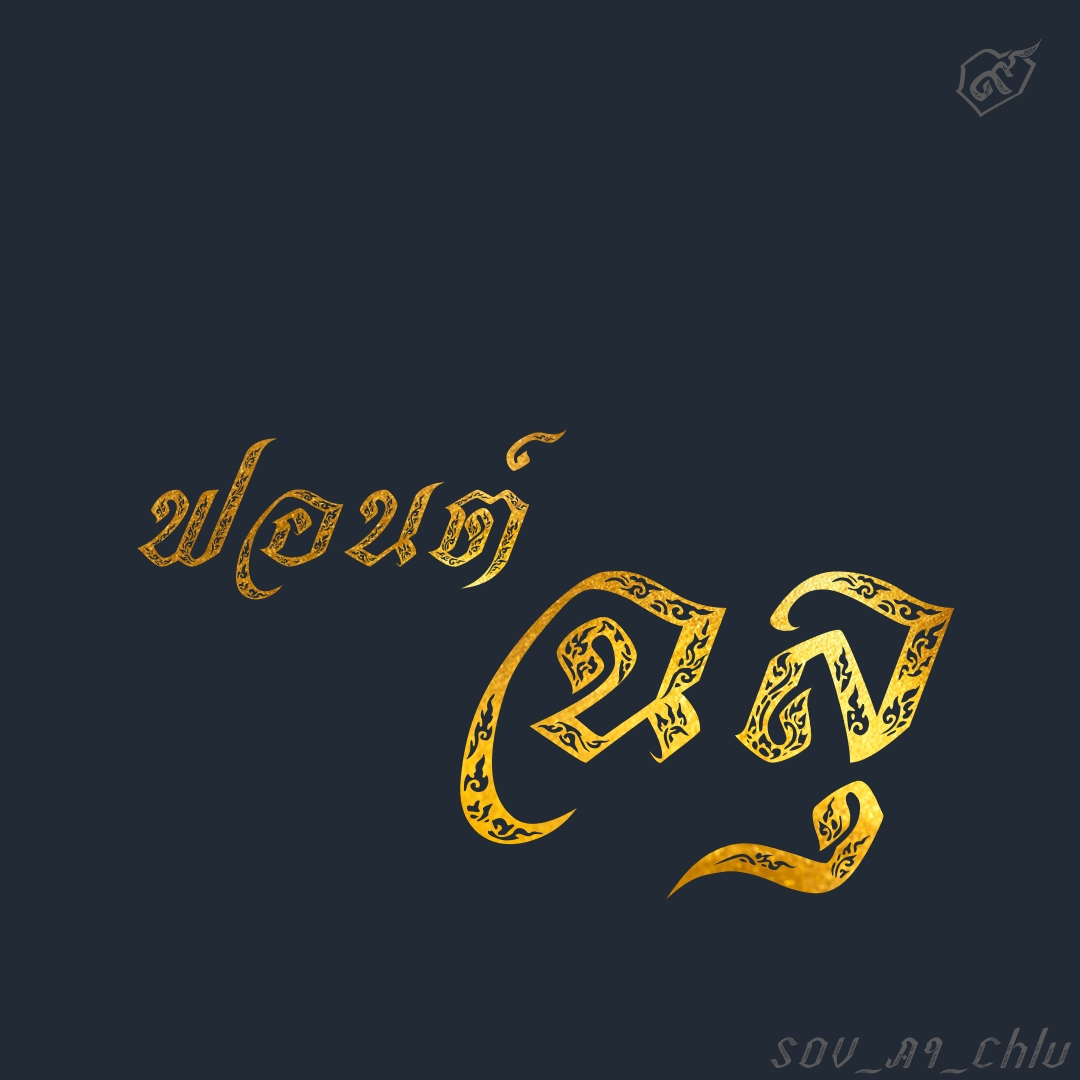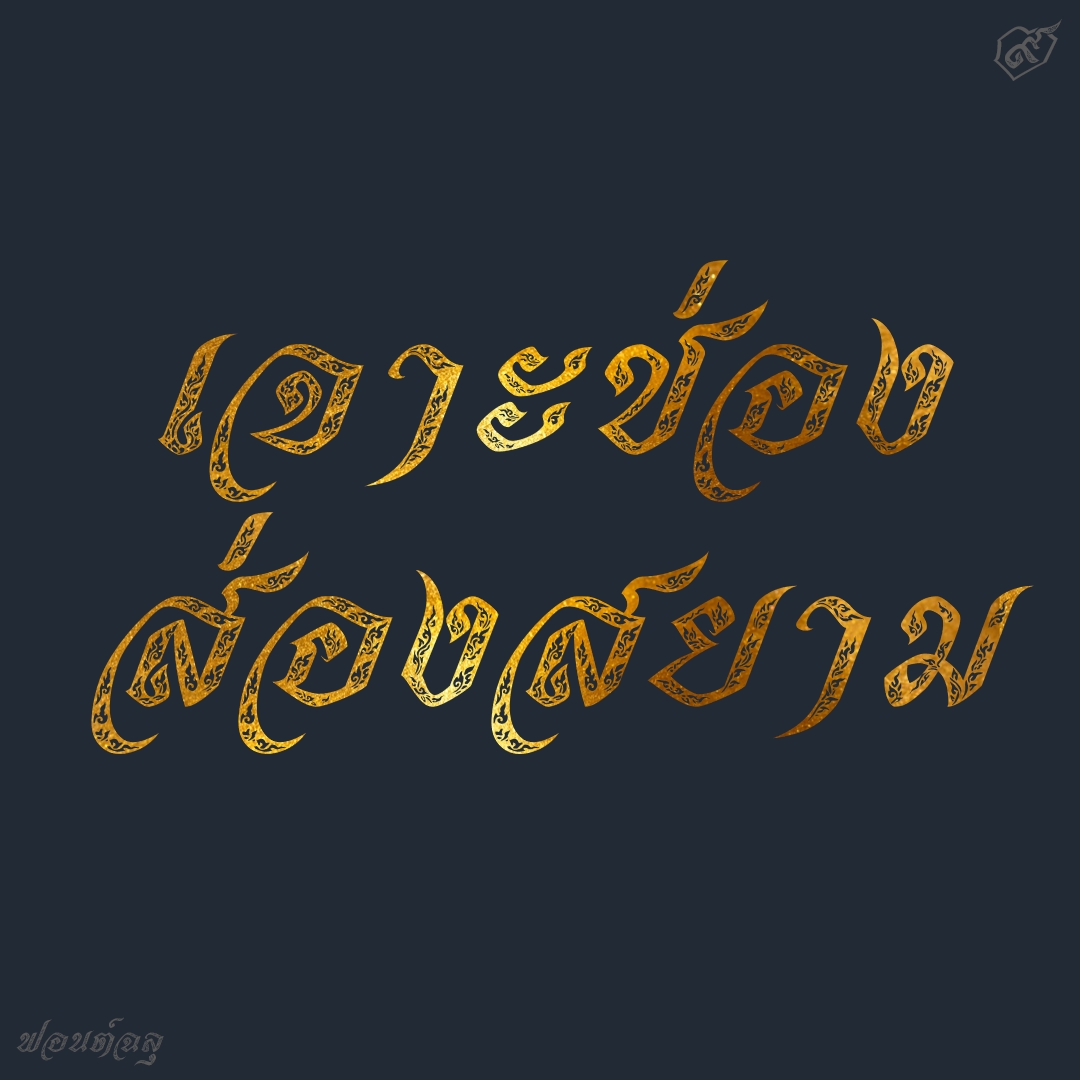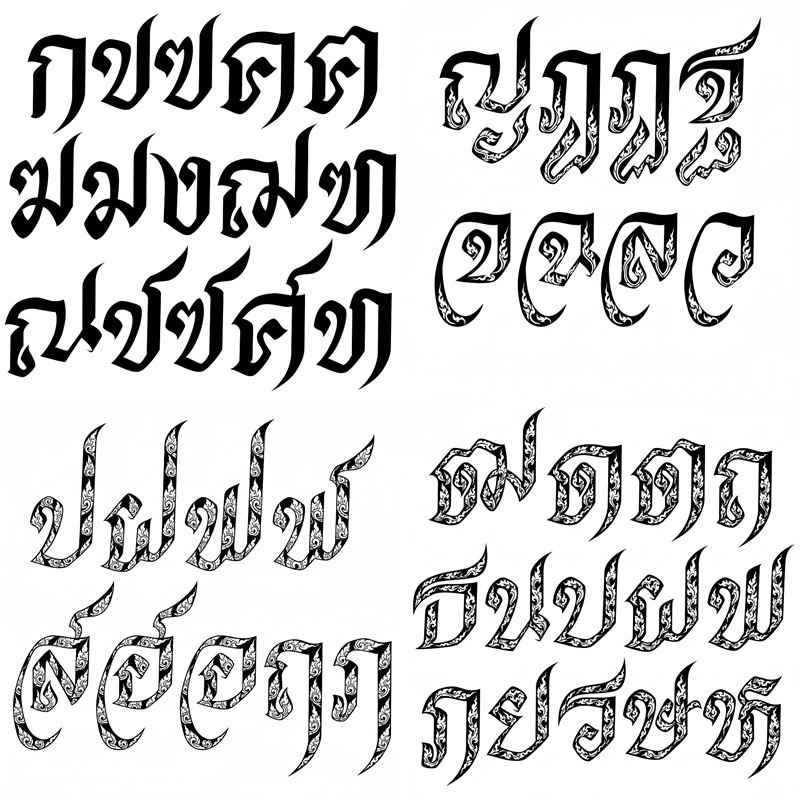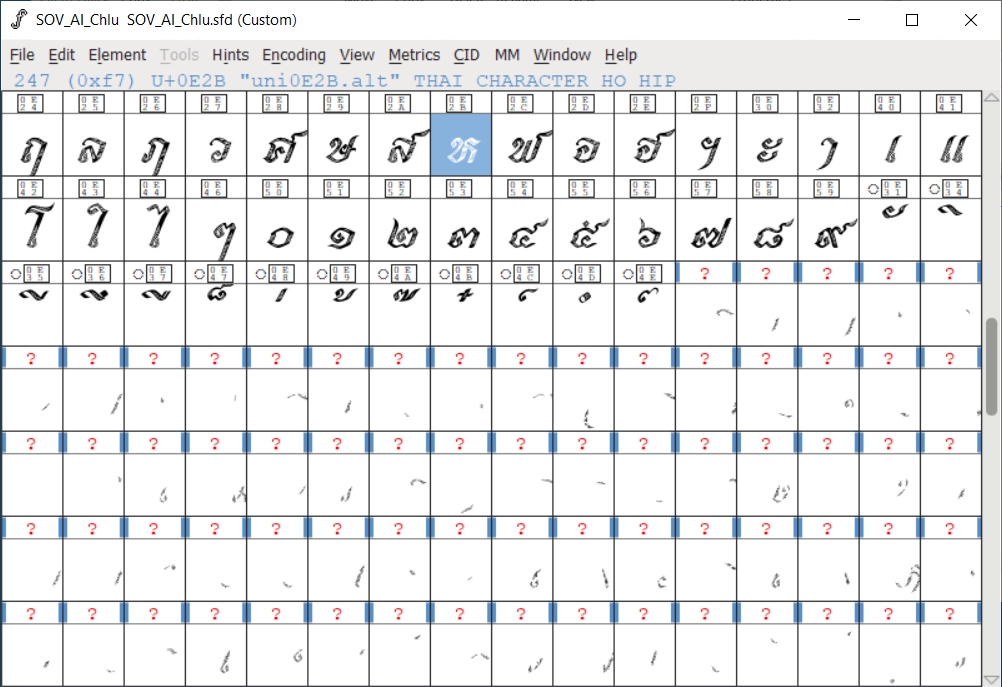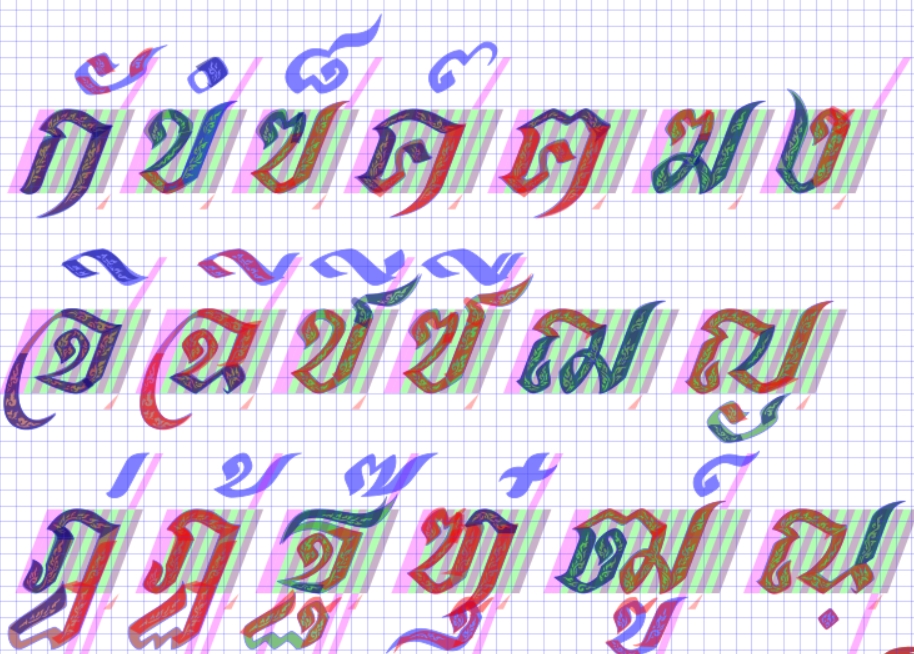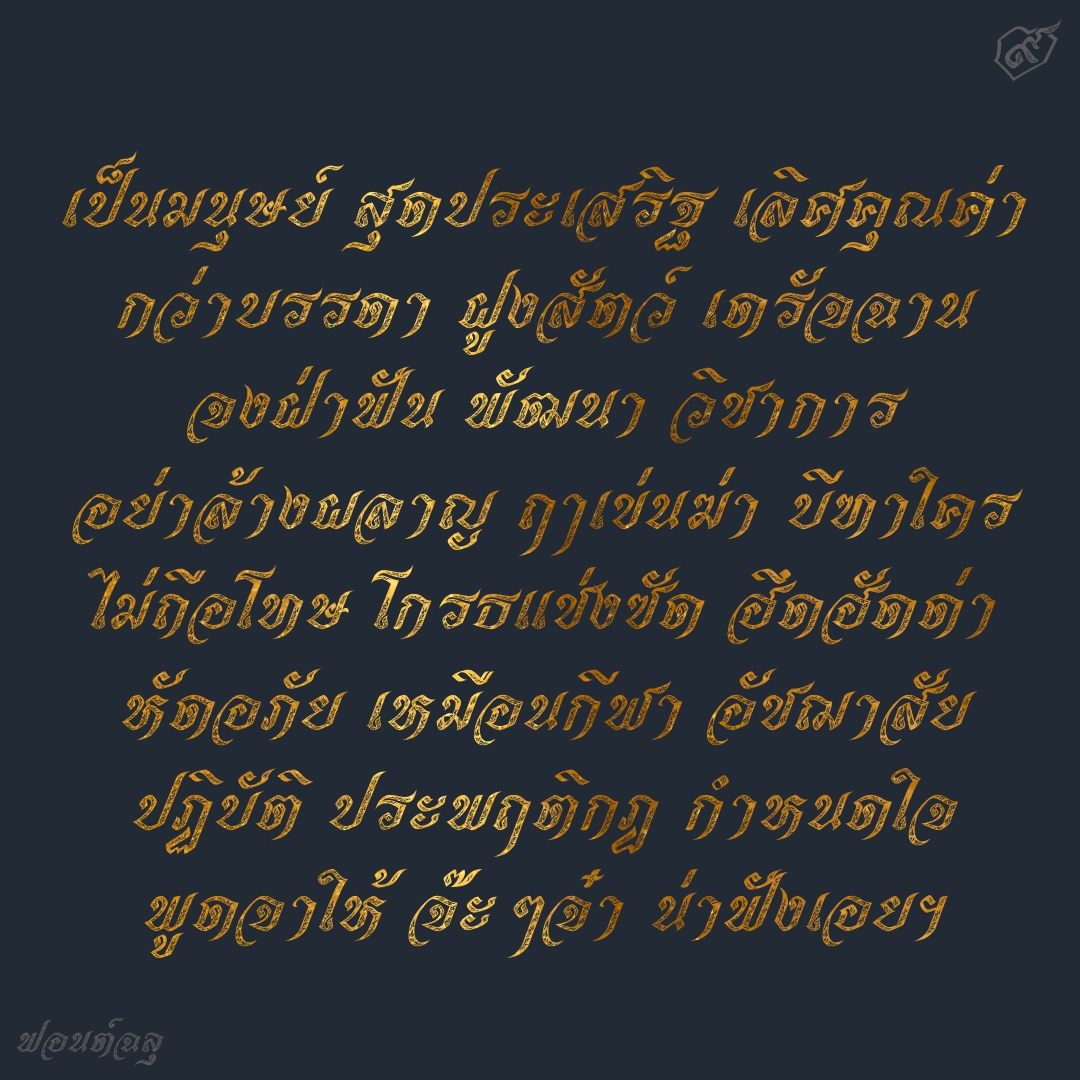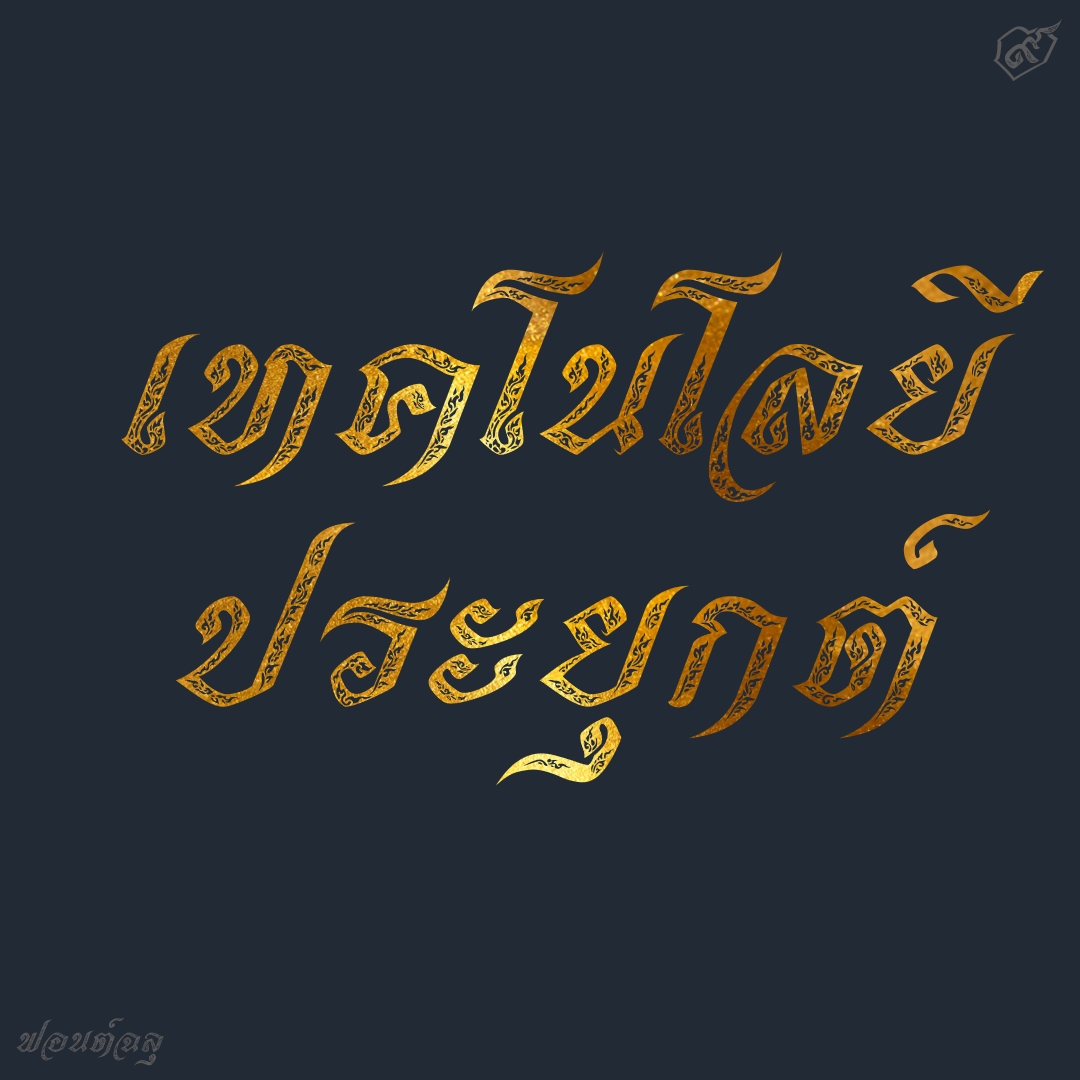
ฟอนต์ ฉลุ
ฉลุ เป็นฟอนต์ทำลองนำ AI มาช่วยออกแบบลาย บนฟอนต์เดิมของเรา..ตะแบงเอียง (SOV_TaBang) แล้วนำลายนั้น ย้อนกลับมาทำเป็นลายฉลุบนฟอนต์อีกที
ชื่อฟอนต์ : ฉลุ
ฉลุ เป็นฟอนต์ทำลองนำ AI มาช่วยออกแบบลาย บนฟอนต์เดิมของเรา..ตะแบงเอียง (SOV_TaBang) แล้วนำลายนั้น ย้อนกลับมาทำเป็นลายฉลุบนฟอนต์อีกที
เล่าเรื่องเบื้องหลัง
เริ่มจากพิมพ์ฟอนต์ตะแบงออกมาเป็นตัวอย่าง แล้วบอกให้ AI gen ลายลงไปในตัวอักษร ดังรูป
ผลที่ได้ออกมาหลากหลาย และไม่สามารถคุมความเสถียรได้ดี (เปลี่ยนไปใช้ JSON prompt ก็ยังไม่นิ่ง)
แต่เนื่องจากรูปทรงอักษร อยู่ในแนวทางเดียวกัน จึงใช้แค่ 2-3 ภาพก็พอเพียง โดยการเอามาตัดเป็นชิ้นๆ แล้วทาบกับอักษรทั้งหมด
พอดูว่าเป็นไปได้แน่ๆแล้ว จึงเข้าสู่กระบวนการทำฟอนต์  โดยทำชิ้นส่วนที่ตัด แล้วเอาไปทาบบนใน font file จริงๆ
แล้วจึง reverse เพื่อให้เป็นการฉลุลายบนตัวอักษร
จบ.. ไม่ต้องจัดอะไรอีก เพราะฟอนต์เดิมทำเสร็จไปตั้งแต่ต้นแล้ว เราแค่ทำกระบวนการฉลุลายลงไปเท่านั้น